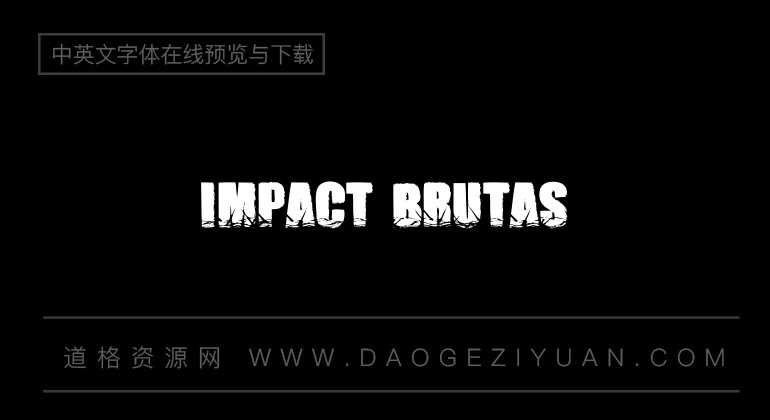
Impact Brutas
Impact Brutas 是一种非常独特的字体,它拥有非常醒目的外观和极具冲击力的设计。它的字母形状非常饱满,轮廓线条非常粗犷,细节部分非常突出,整体上非常适合用于大标题和短语。 这种字体最初由设计师 Eduardo Recife 创作于2005年,它是他的一系列手写风格的字体中的一种。Impact Brutas 经常被用于海报、包装和广告等领域,因为它的设计非常醒目,可以很好地吸引人们的注意力。
Impact Brutas是一款非常不错的手写艺术字体,具有很好的视觉感,适合于文化类的宣传设计、商业类品牌的广告和产品包装设计以及个性化文字排版等较多场景。